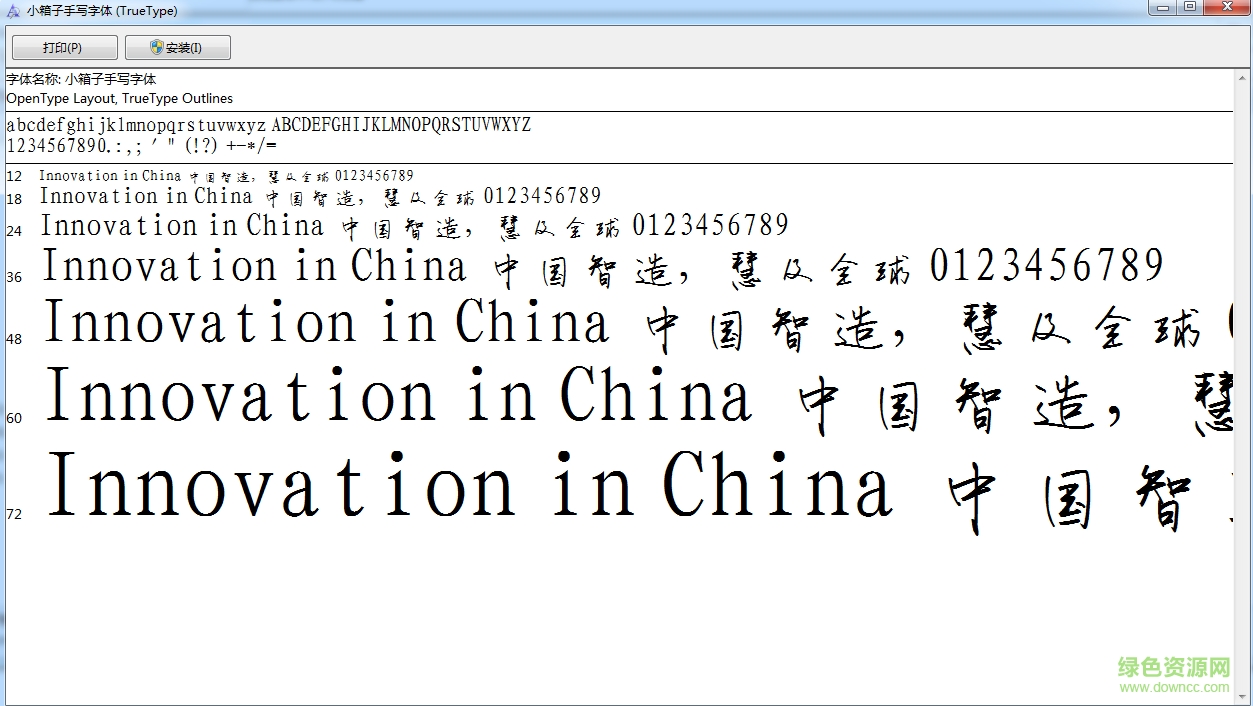
小箱子手写字体
小箱子手写字体是一款TTF格式的手写字体,是作者林哲祥自创的行草字体,简洁清爽的书法让你阅读观赏更加愉悦,喜欢的朋友快来绿色资源网下载吧!
字体介绍
手写字体一直都是信筏书签,设计美工的左膀右臂。但在这个互联网时代,手写的字体虽然小众,却一直是以不可磨灭的重要意义存在。其一中国书法文化博大精深,历史源远流长。其二就是与众不同的个性化。所谓:阴影越是丰富,立体感越强。在普罗大众眼里“与众不同”就是一种个性化。
基于自身书法功底,以行楷手写这套字体,在制作字体库的时候,对字体大小和位置进行微调,这样输入时字体视觉上会错开 ,呈现出来的书写效果更接近真实手写。
近期将完成个人的第二套行草字体,达到常用词组字体之间“笔断意连”的行云流水效果。也借此平台希望把个人对书法、手写字体的理解传递给懂得欣赏的人、需要的人。